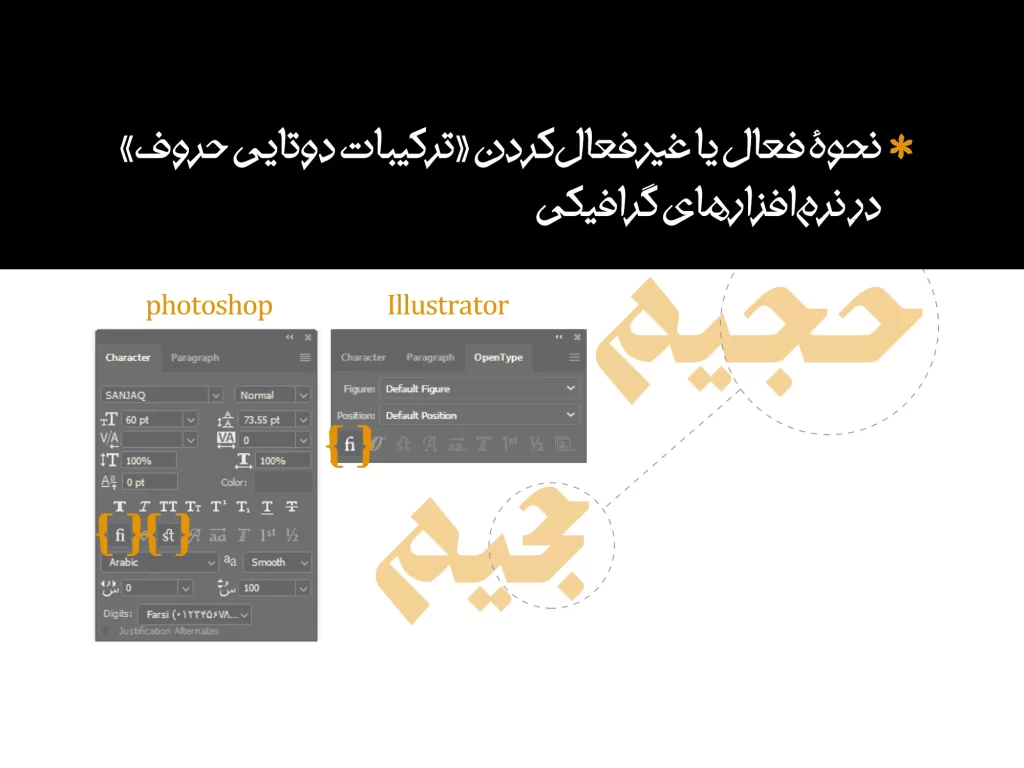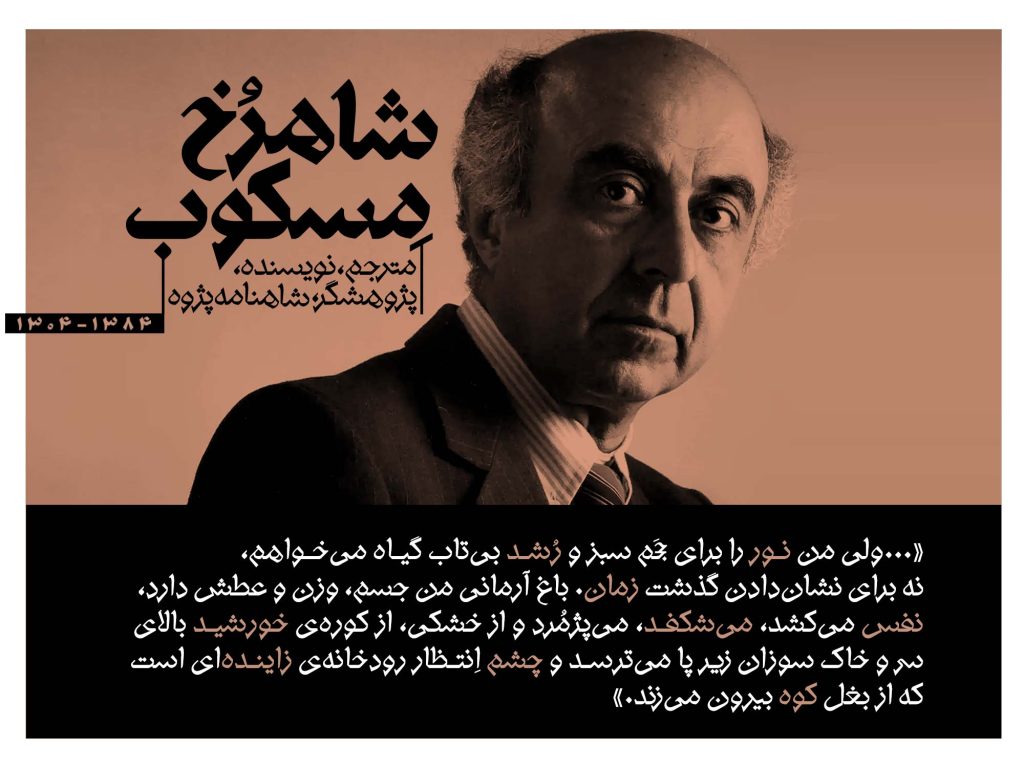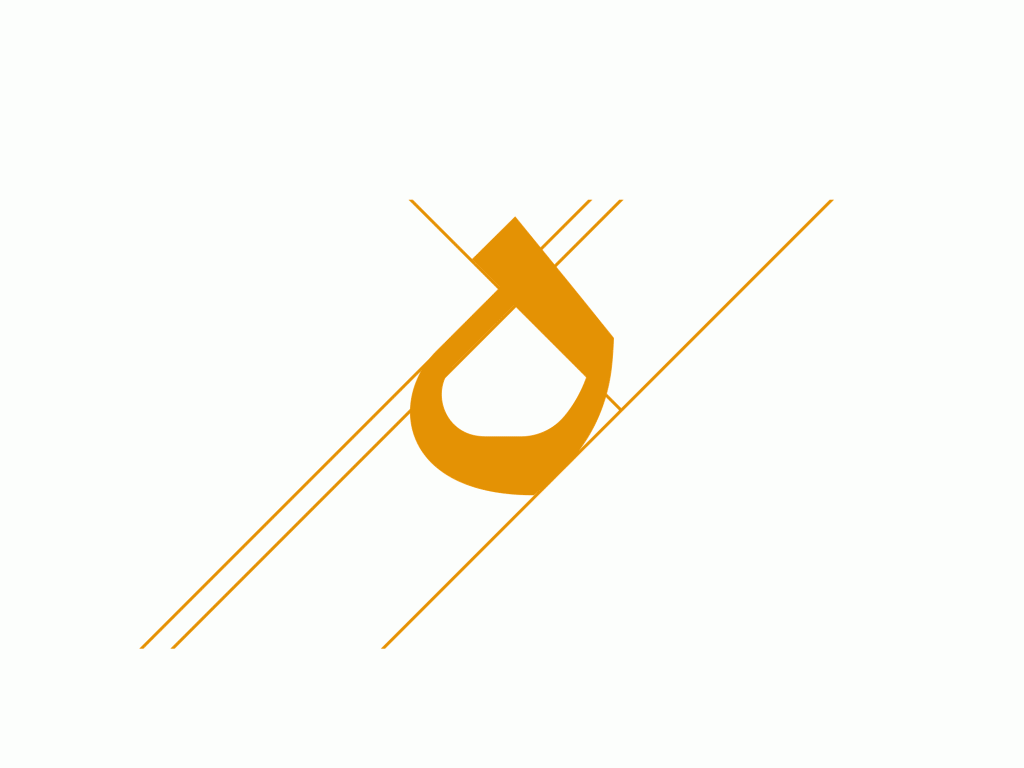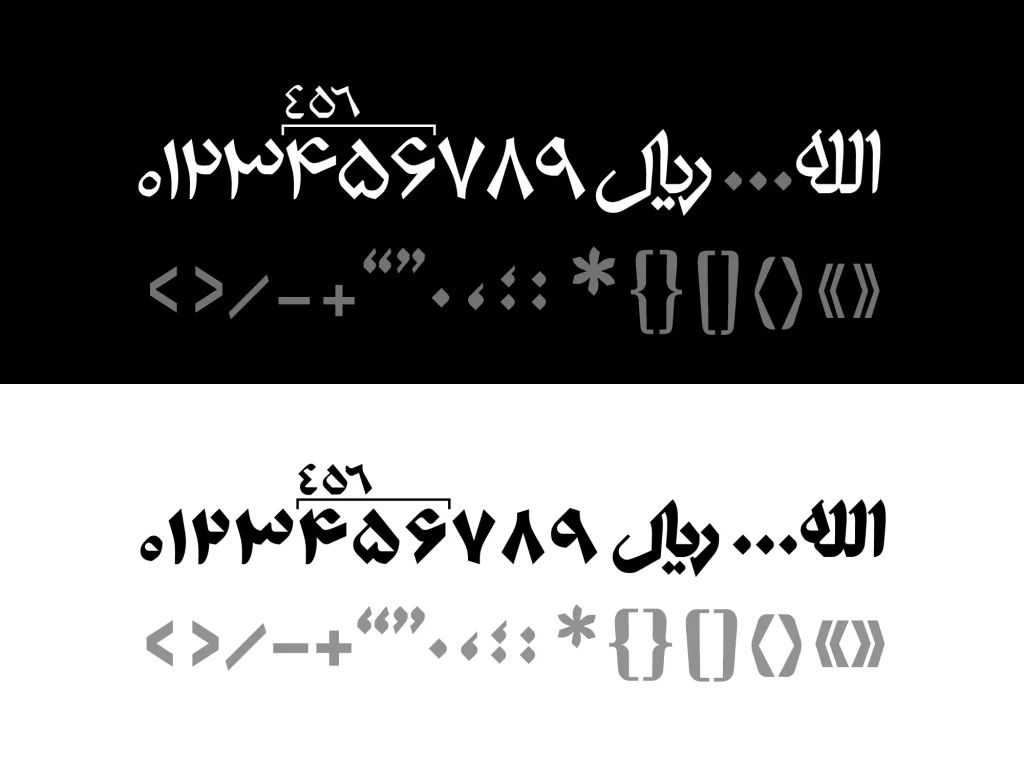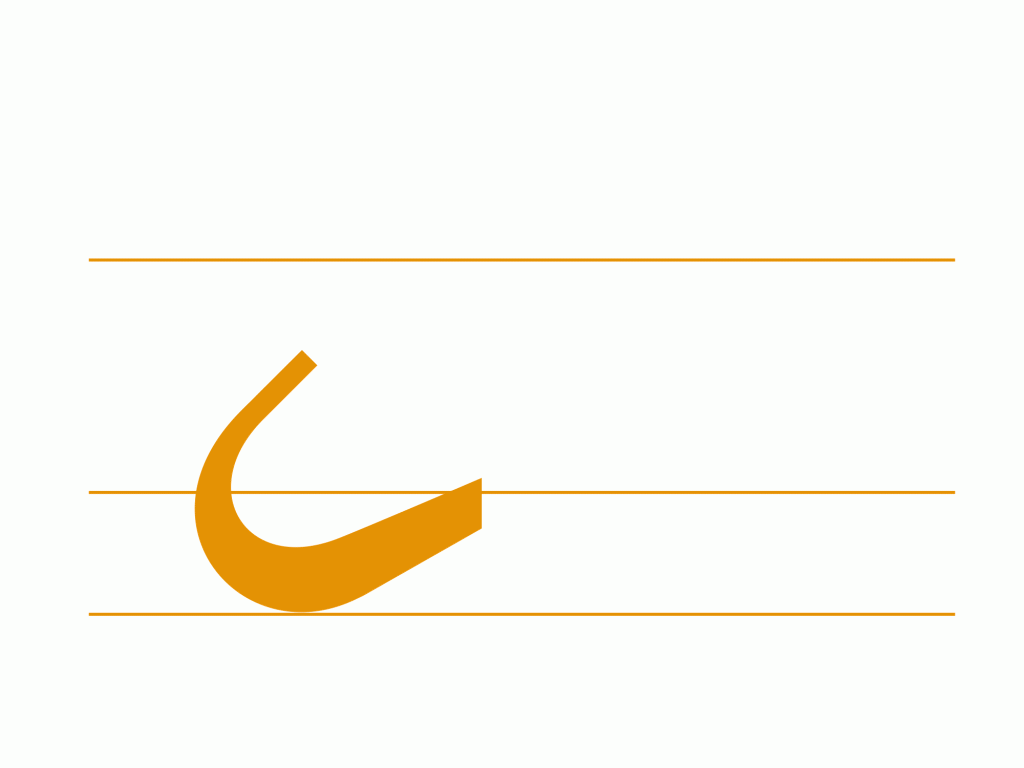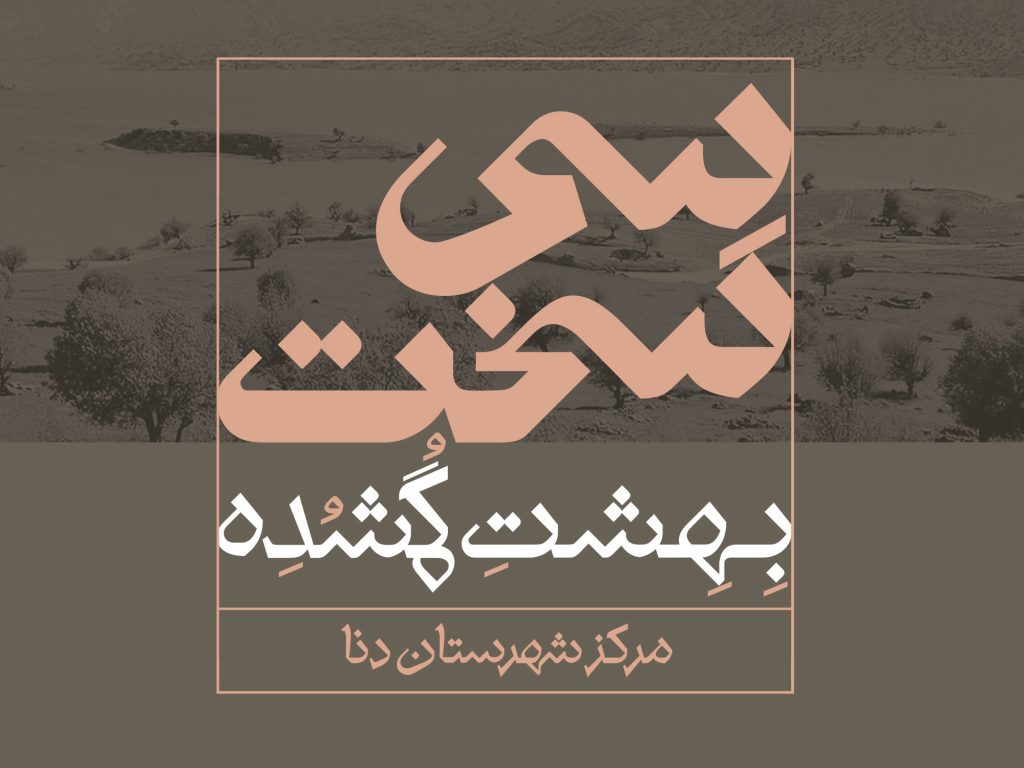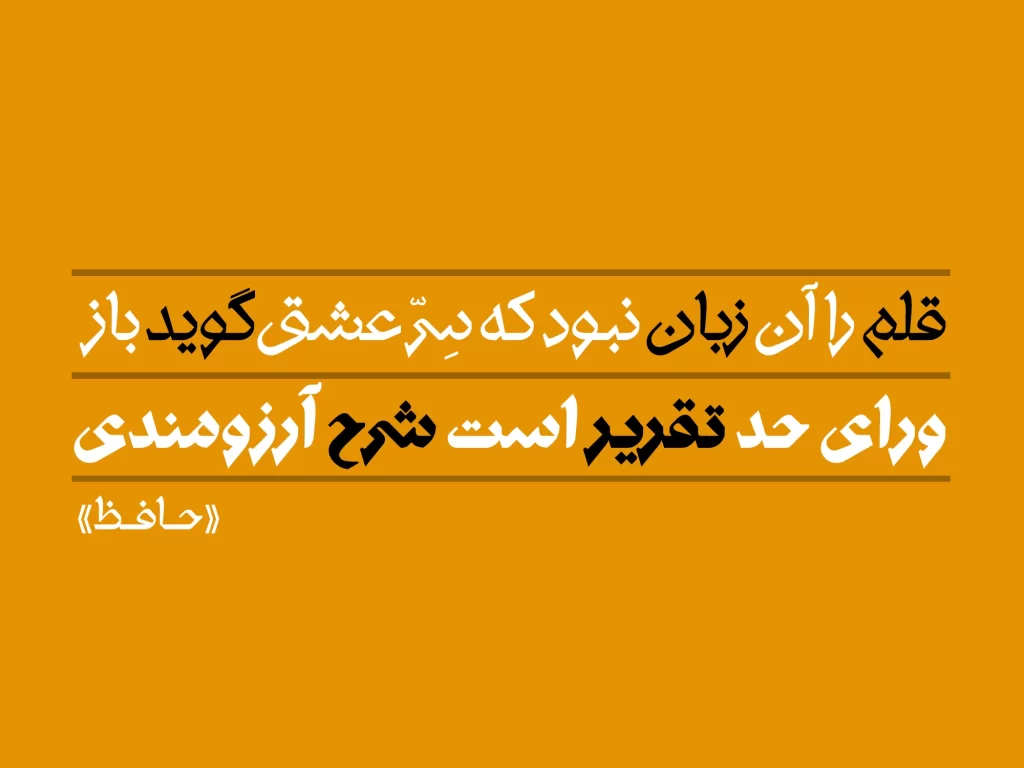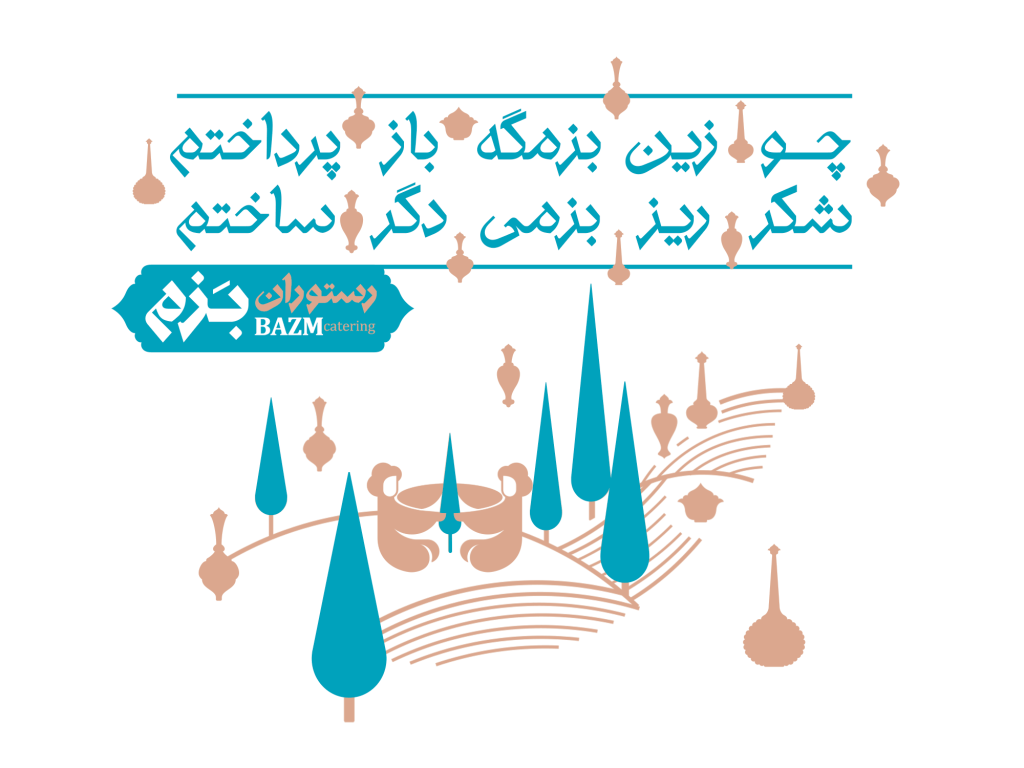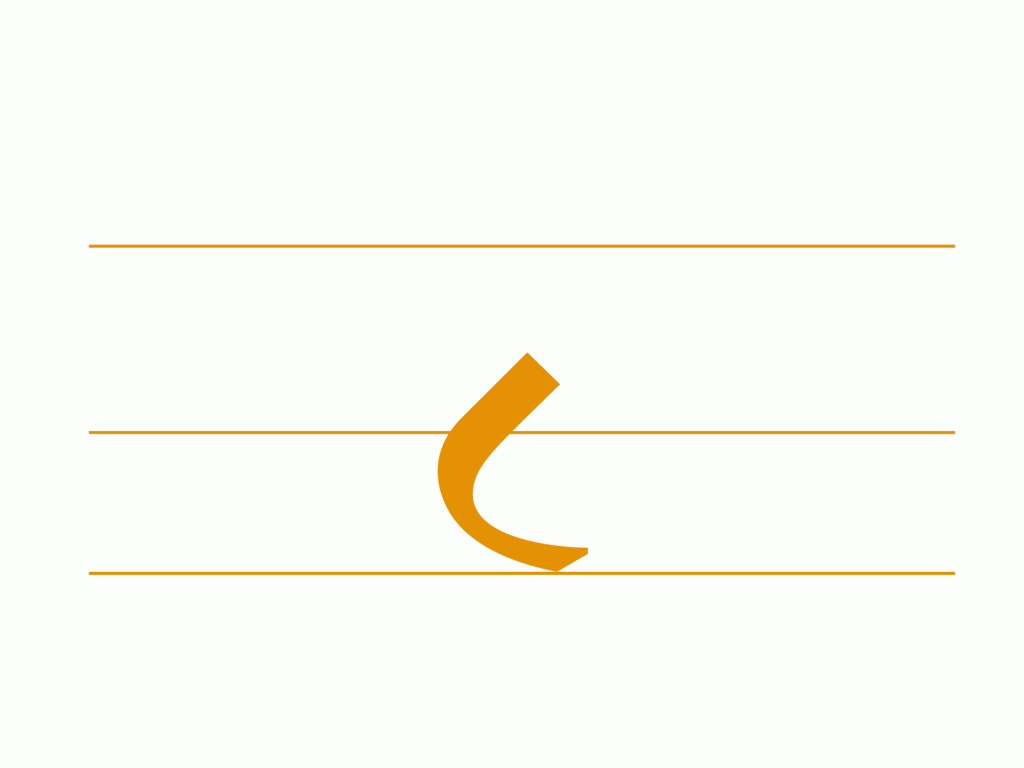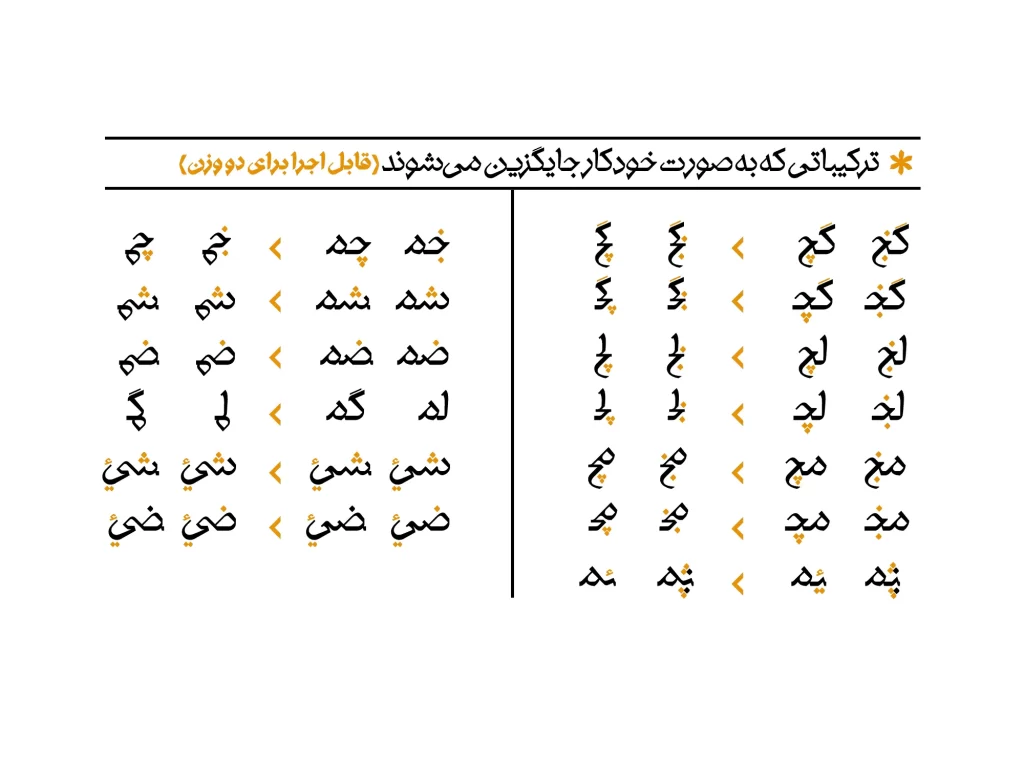
فونت سنجاق
فونت سنجاق با الهام از فرم سنجاق بدست آمده است. همه می دانسم سنجاق تشکیل شده از منحنیها، تیزیها و شکستگیها با ضخامتهای نسبتاً پر کنتراست است. خطوط شکسته و اریب عمدتاً با زوایای چهل و پنج درجه در اتصال به منحنیها، فرمی شجاعانه و در عین حال چابک را برای این شکل قلم فارسی ایجاد کرده است.
هر بخش از آناتومی حروف بر اساس یک الگو یا مبنای ثابت فرمی طراحی شده است: به بیانی روشن تر، تمامی قوسهای مثبت (ص، ن، ل، ی…) تمامی قوسهای منفی (ع ،ح …)، تمامی خطوط عمود (ا،ط،ل …)، تمامی چشمیها (ه، م،) و … در دستۀ خود مشابه یکدیگرند. این خصیصه در کنار زوایا، قوسها و پایانههای یکسان حروف، باعث نظم هندسی بیشتر فونت سنجاق شده است.